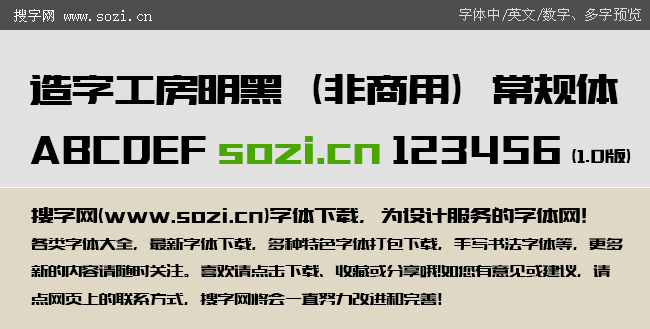
造字工房明黑(非商用)常規(guī)體
搜字網(wǎng)提供一款造字工房明黑(非商用)常規(guī)體中文字體下載,造字工房明黑體字形扁平,筆畫清晰而飽滿,厚重工穩(wěn),遒勁有力,剛毅而不失俊朗,且直角的處理更顯剛毅,有極強(qiáng)的視覺表現(xiàn)力。此款字體適用于主副標(biāo)題及個(gè)性品牌的設(shè)計(jì)等應(yīng)用。